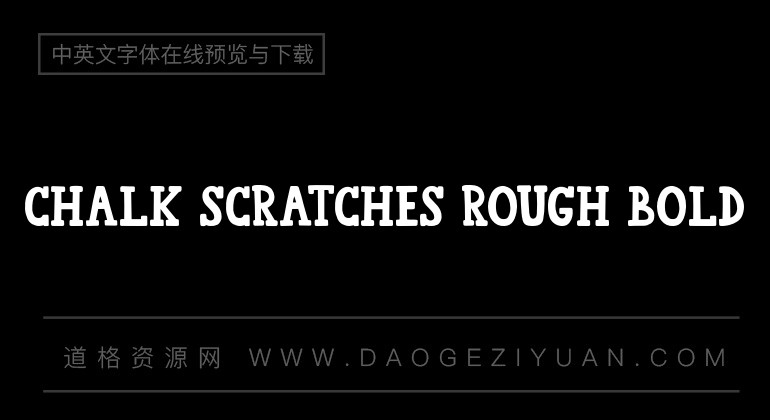
Chalk Scratches Rough Bold
Chalk Scratches Rough Bold 是一种手写风格的字体,具有粗糙、鲜明的特点。这种字体的设计灵感来自于黑板上用粉笔书写的手写字体,增加了手写感和文艺气息。此外,该字体还具有一些独特的设计特点,例如字母之间的距离较小,让整个字体看起来更加紧凑,同时也更加清晰易读。 这种字体适用于许多不同的场合,例如广告、海报、宣传单、手工艺品等等。该字体的使用可以为这些设计带来一种独特的手工感和艺术氛围,让设计更加个性化和有吸引力。
Chalk Scratches Rough Bold是一款非常不错的手写艺术字体,具有很好的视觉感,适合于文化类的宣传设计、商业类品牌的广告和产品包装设计以及个性化文字排版等较多场景。
Chalk Scratches Rough Bold字符映射图